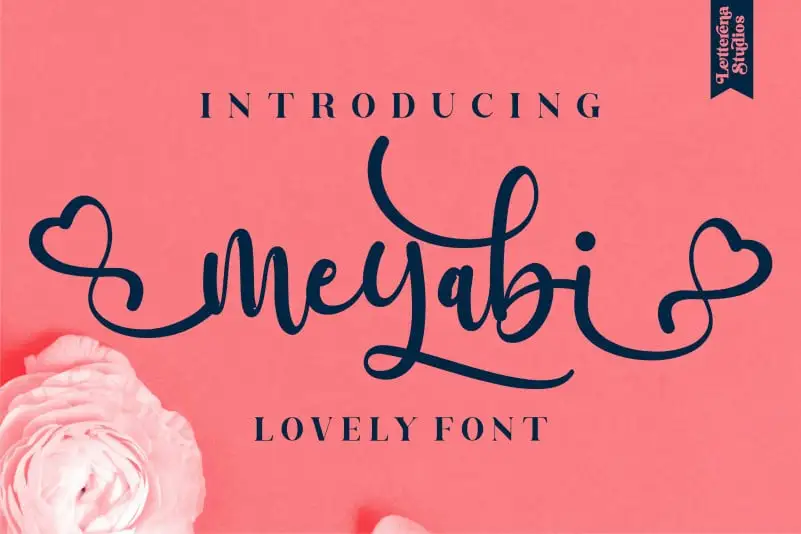
Meyabi Script Font – Fonte Grátis
Meyabi Script Font
Meyabi Script Font é uma elegante fonte escrita à mão ideal para qualquer projeto que busque um toque romântico e sofisticado. Desenvolvida pela Letterenastudios, essa fonte é perfeita para criações como logotipos, projetos de marca, design de móveis, embalagens de produtos, copos, frases, cartazes, sacolas de shopping, camisetas, capas de livros, cartões de nome, cartões de convidado e convites, etiquetas e até mesmo para adicionar um toque especial à sua imagem de fotografias. Suave e envolvente, ela se adequa perfeitamente a todos os seus projetos que precisam de uma pitada delicada e única do mundo da escrita à mão.